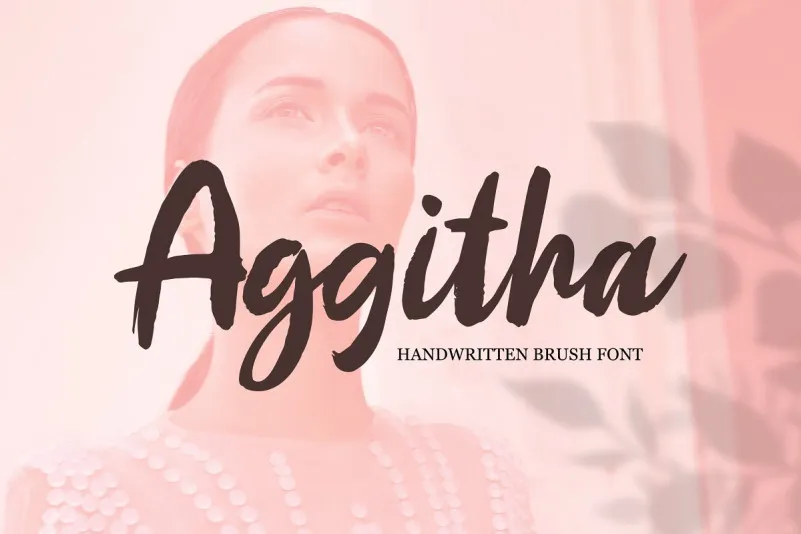
Aggitha Brush Font – Download Grátis
A Aggitha Brush Font é uma fonte escrita a mão que encanta com seus traços levemente texturizados, inspirados na arte dos pincéis naturais. Desenvolvida pelo designer Weape Design e apresentada pela bafonts, esta font se destaca por oferecer um equilíbrio entre modernidade suave e estilo elegante. Suas linhas naturais, que se parecem com os movimentos rápidos de uma caneta a óleo sobre papel, criam um aspecto belamente natural, perfeito para uso em assinaturas, marcas de marca, no título de casamento, na fotografia, como legenda de revistas e anúncios, capas de livros ou embalagens. Além disso, sua elegância a torna uma escolha excelente para cartões de agradecimento e campanhas publicitárias. A Aggitha Brush Font é um convite aos amantes da arte digital e do design gráfico para experimentar a versatilidade desta fonte única.